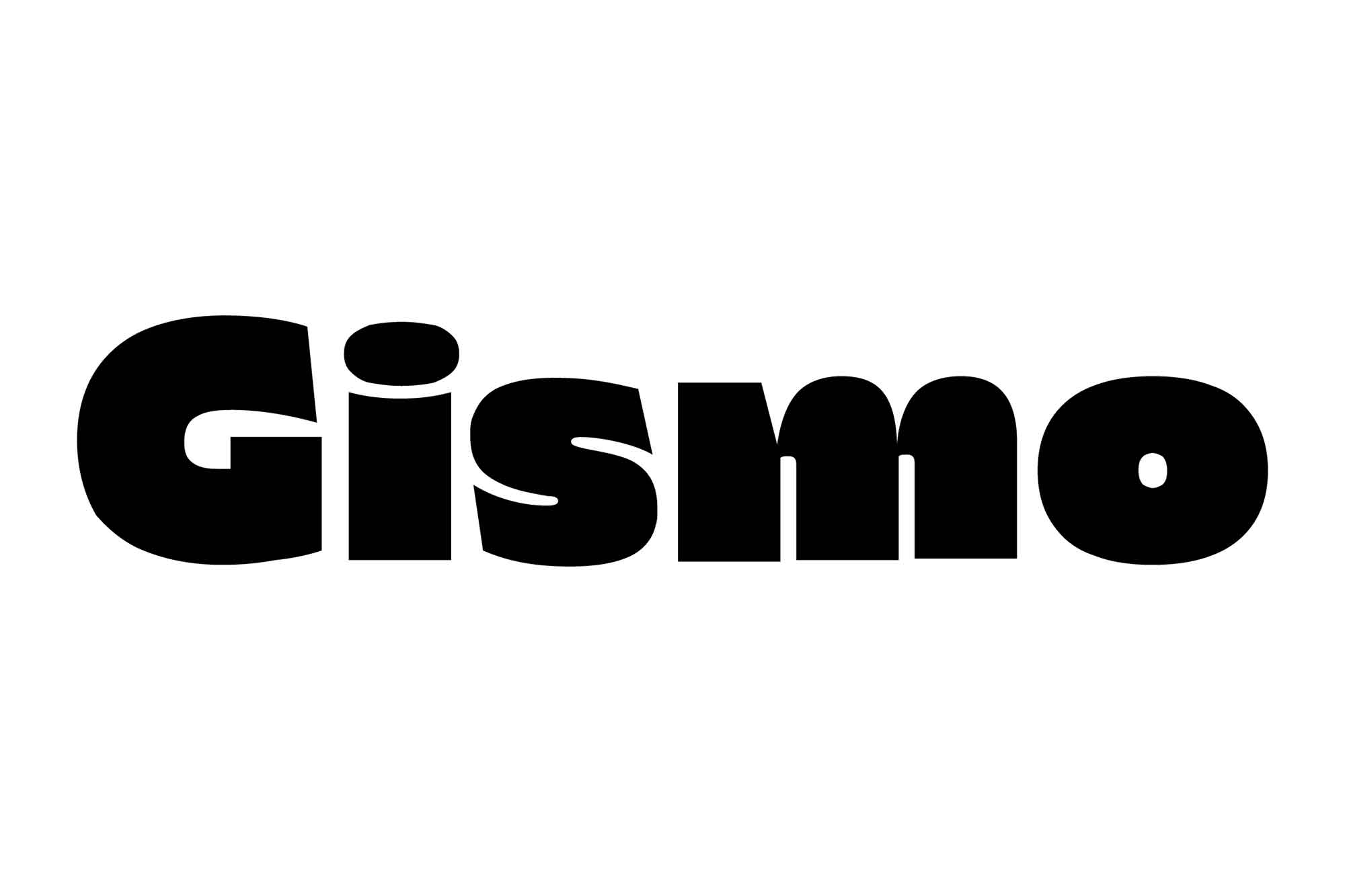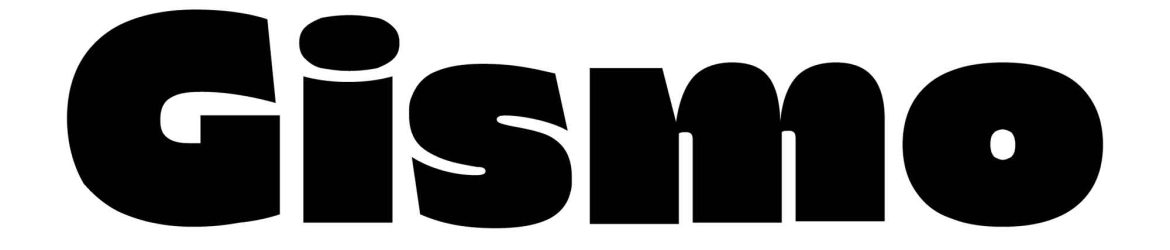
A Gismo é uma família de fontes sans-serif de cinco estilos, conhecida por seu corpo robusto e caracteres que são mistos de forma arredondada e quadrada. Esta fonte conta com 671 glyphs e oferece suporte a 106 idiomas, ideal para projetos variados, como lifestyle, moda e tecnologia. Com um aspecto moderno e versátil, a Gismo se encaixa perfeitamente em ambientes que valorizam design minimalista e simplicidade. Ela é uma opção perfeita para projetos digitais que buscam uma solução de fonte moderna e eficiente, sem perder a elegância e a precisão que o design gráfico precisa. Seja para criar uma identidade visual robusta e atraente, ou para criar um design de produto minimalista e sofisticado, a Gismo é uma escolha inteligente para projetos futuros.